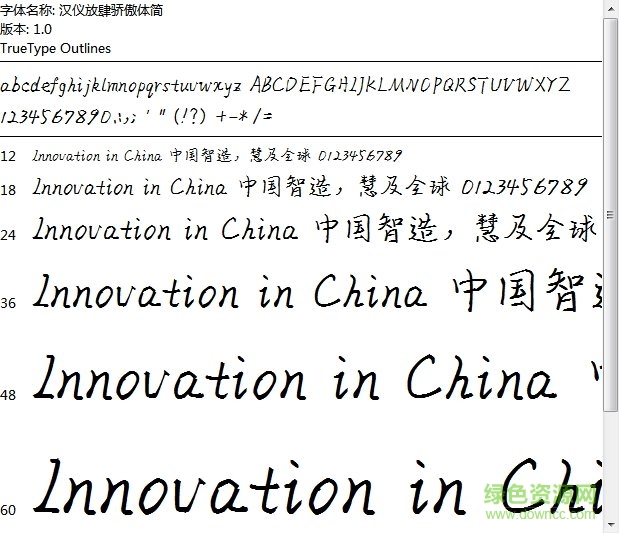
放肆驕傲字體ttf是一款源自于手機qq里的個性手寫字體,與漢儀晨妹子字體比較接近,字跡鋒利而不尖銳、穩(wěn)重而不失灑脫之風,喜歡的朋友就來綠色資源網(wǎng)下載吧!
不要太在乎一些人!
我依然可以驕傲放肆的笑!
追尋心中的信仰!
放肆驕傲體有著簡約流暢的筆觸,字跡雋永清秀、筆畫清晰大方,給人清爽的視覺呈現(xiàn),可以廣泛運用于平面設計、logo設計、書信排版、海報設計等諸多場合!